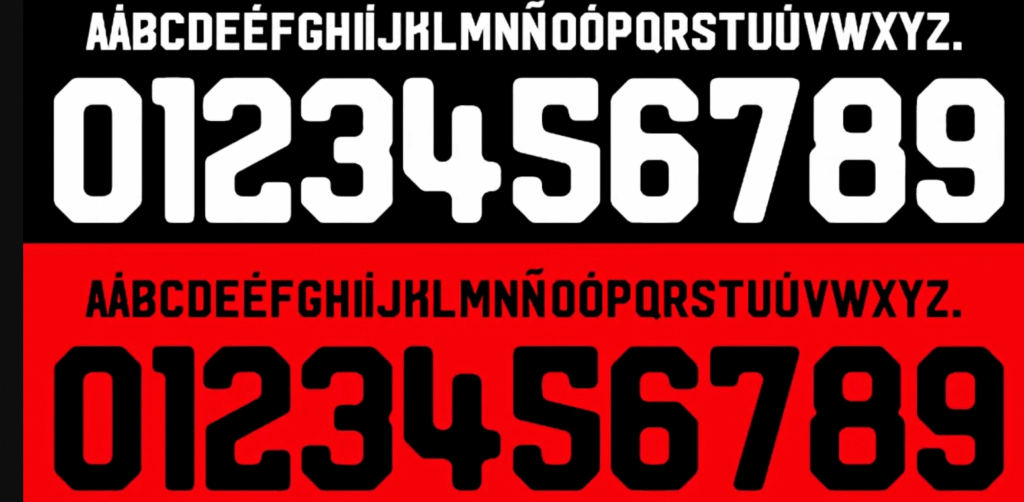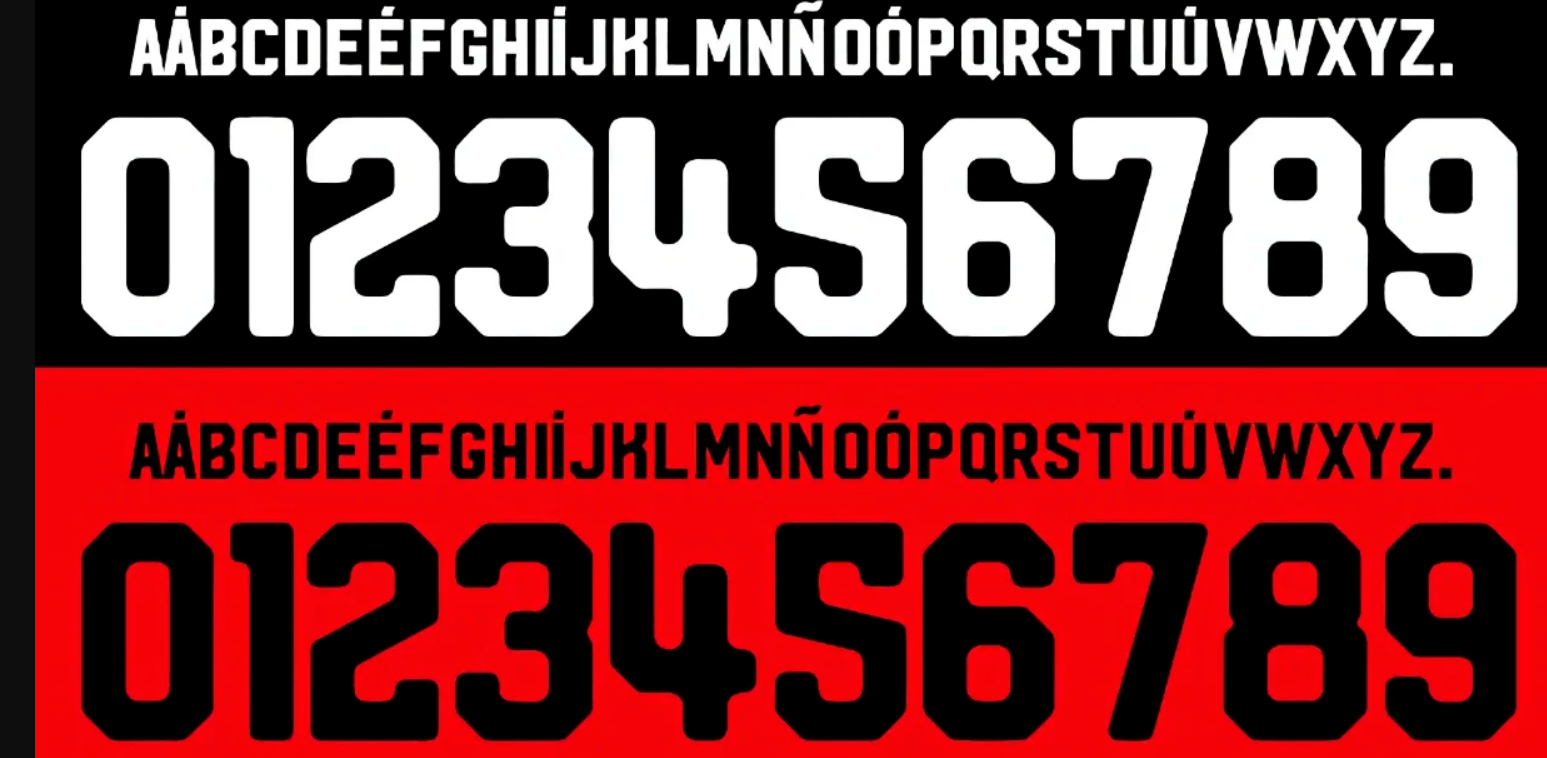
O ano de 2023 ficou marcado para sempre na história do São Paulo FC. Foi o ano da redenção, da campanha emocionante e da inédita conquista da Copa do Brasil, um título que lavou a alma do torcedor tricolor. E para eternizar esses momentos, a Adidas, fornecedora de material esportivo do clube, desenvolveu uma tipografia marcante que estampou os nomes e números dos heróis dessa jornada.
- Usos Recomendados: Ideal para criação de mockups de camisas, artes para redes sociais (posts, stories), banners, vídeos e qualquer projeto gráfico que exija a identidade visual do Tricolor campeão de 2023.
Estilo Visual: A Marca do Campeão
A tipografia desenvolvida pela Adidas para o São Paulo em 2023 é moderna, limpa e imponente. Ela apresenta um design robusto, com cantos ligeiramente chanfrados (cortados) que dão uma sensação de movimento e agressividade. Os números são largos e de excelente legibilidade, garantindo visibilidade máxima tanto no campo quanto em peças gráficas.
É uma fonte que transmite seriedade e força, perfeitamente alinhada à tradição do clube. Foi com ela que os nomes de ídolos como Calleri, Luciano, Lucas Moura e Rodrigo Nestor foram gravados nos mantos da campanha vitoriosa da Copa do Brasil.